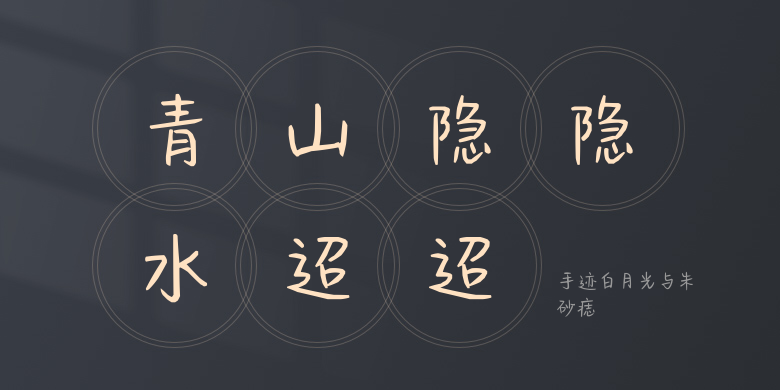
手迹白月光与朱砂痣
手迹白月光与朱砂痣,这款字体结构工整、笔画清晰,兼顾美观与易读性,适用于标题、正文、海报、包装、LOGO 等多种场景。字形优雅稳定,风格百搭耐看,适配日常排版与创意设计,让文字呈现更舒适、更具质感。手迹白月光与朱砂痣一笔一画,皆是细节,以均衡的比例、流畅的线条打造舒适视觉体验,字形端正大气,风格简约现代。无论是商业设计、品牌宣传还是日常排版,都能轻松驾驭,让文字更有格调与力量。手迹白月光与朱砂痣字体下载。